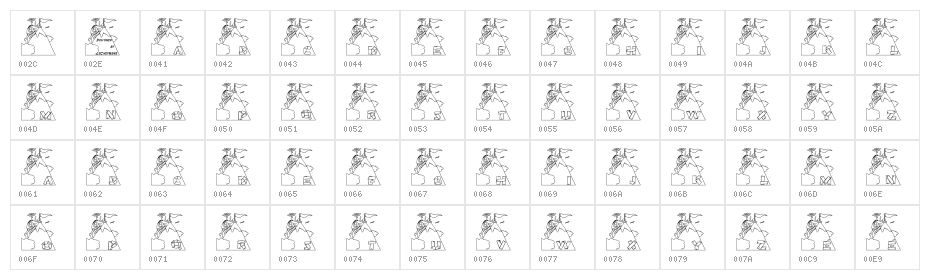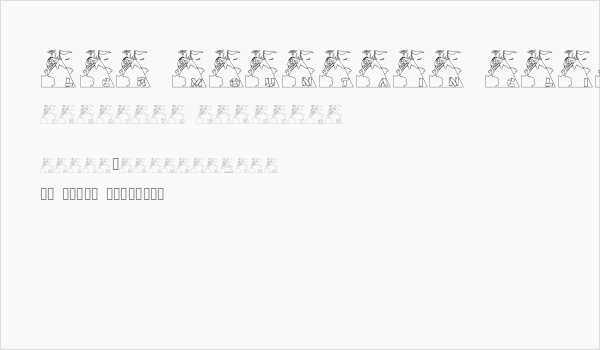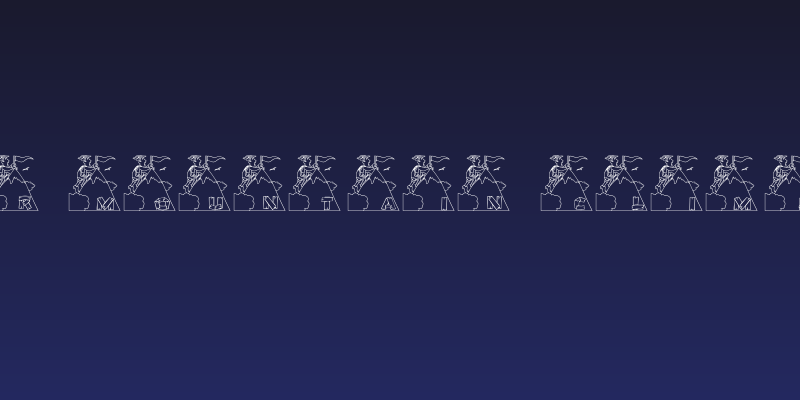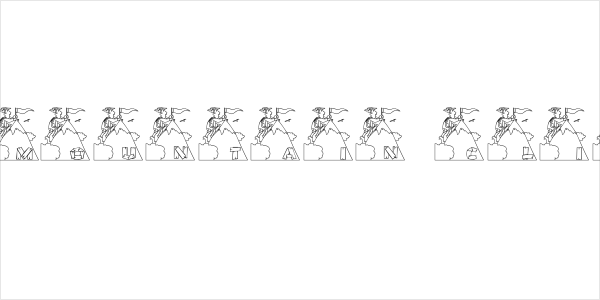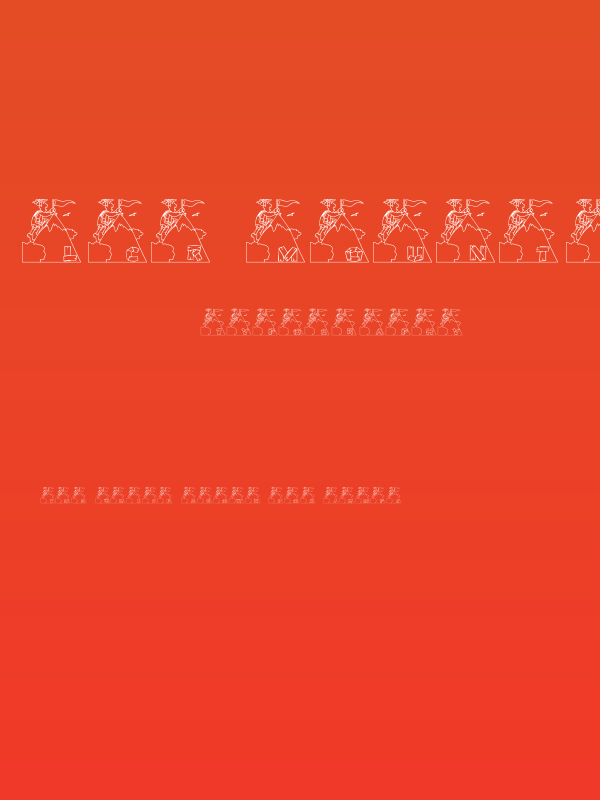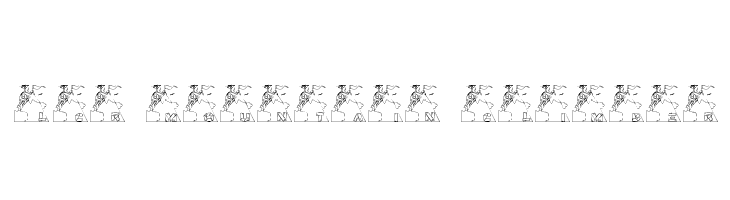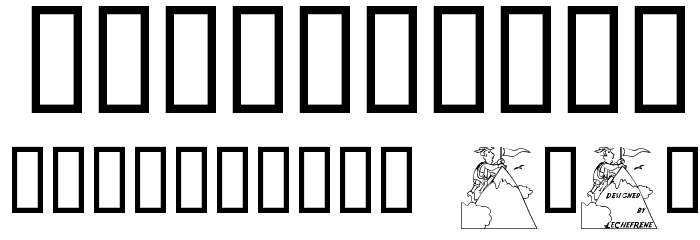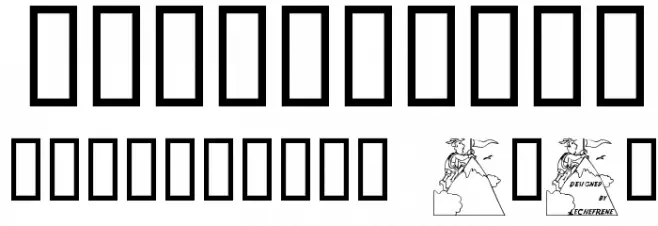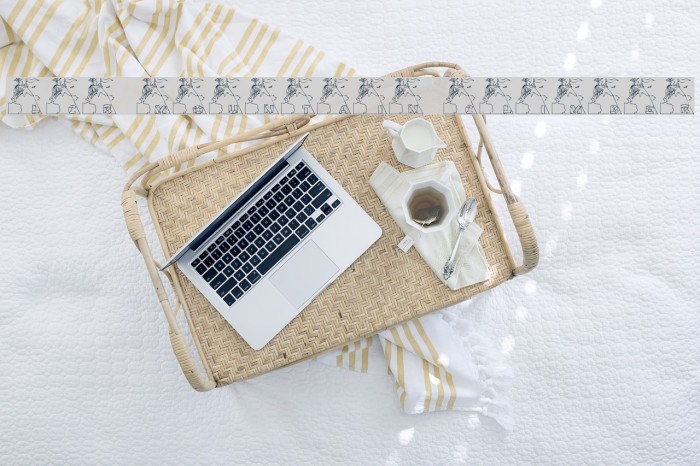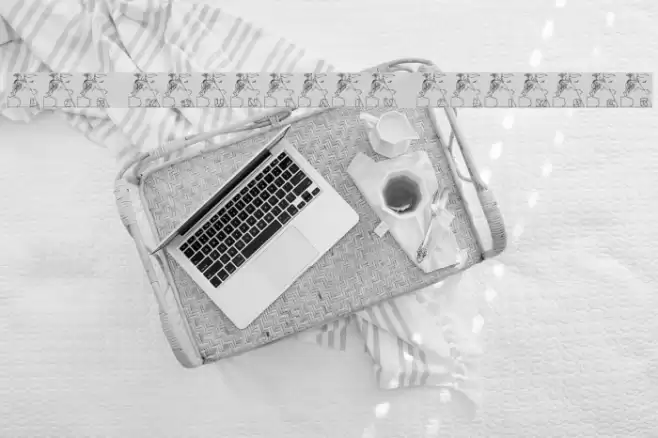
LCR Mountain Climber Font
| Anwendungsfall | Headlines, Artistic projects, Thematic displays |
| Vorgeschlagene Projekte | Ideal for adventure-themed posters, outdoor event branding, or artistic projects that require a strong visual theme. |